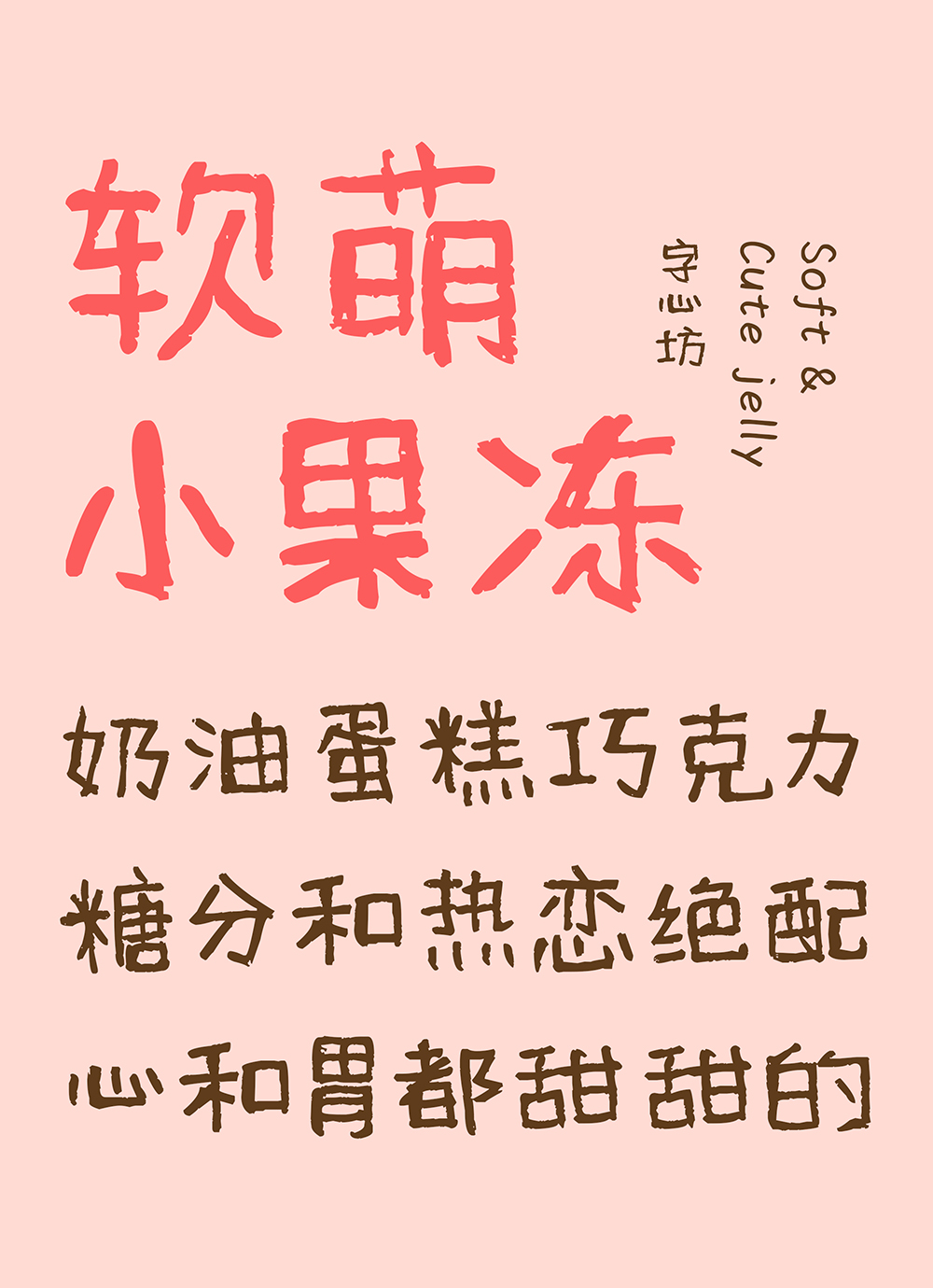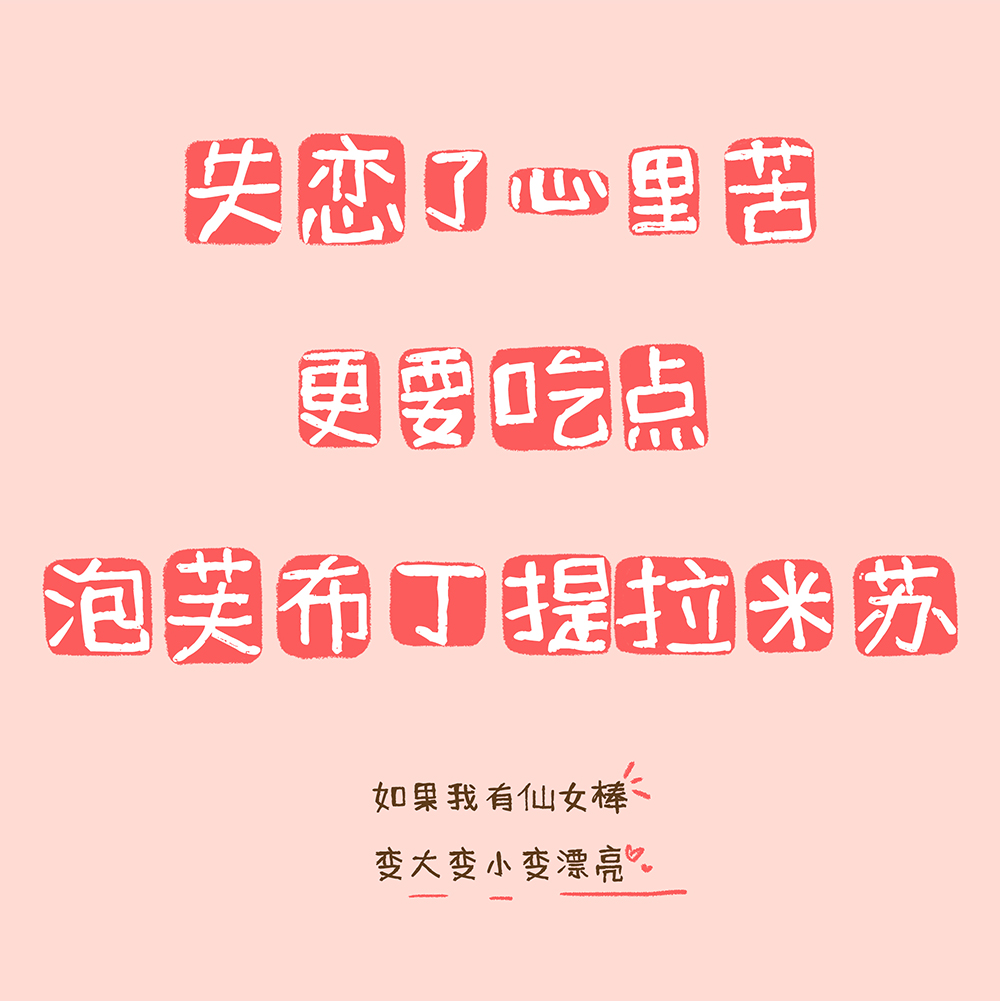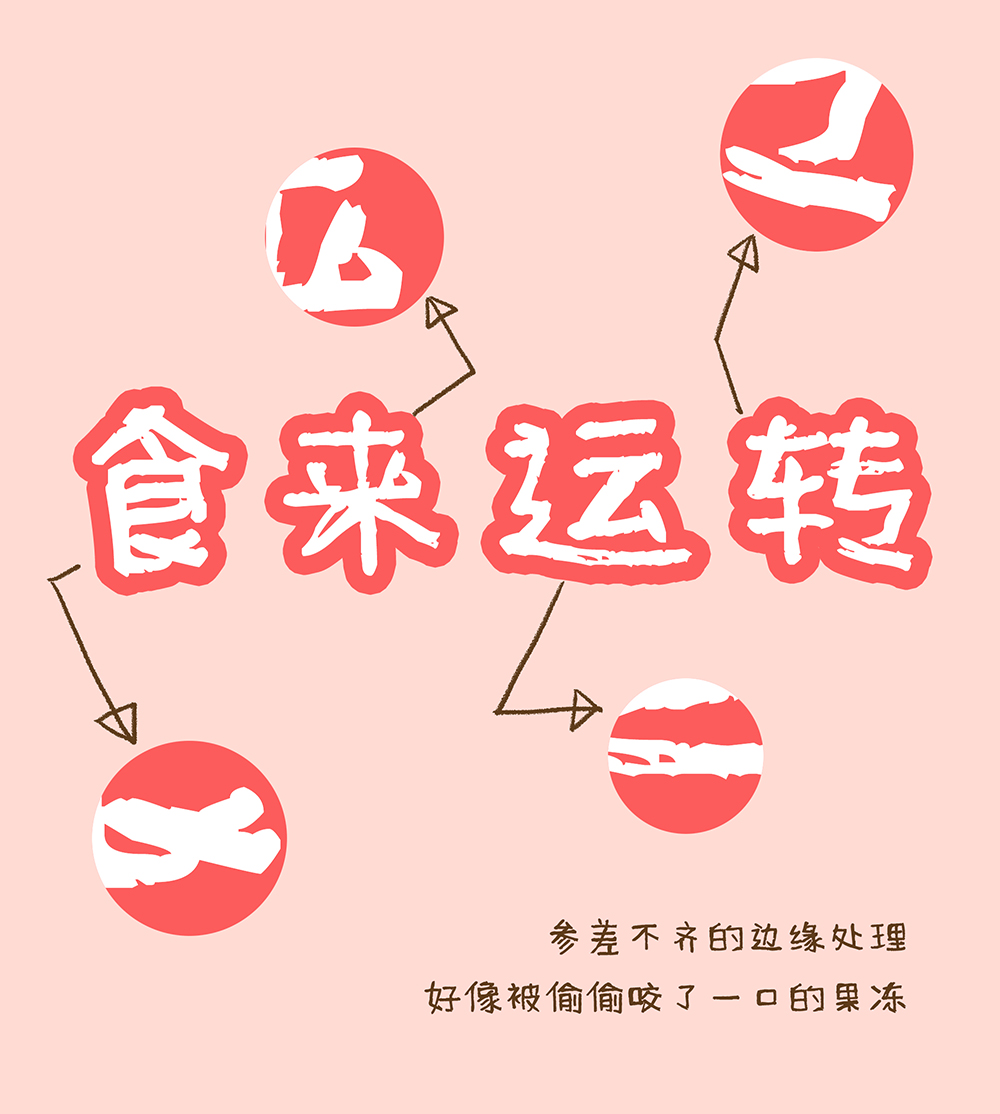
字心坊软萌小果冻
该字体为书法作品,可爱软萌、个性、小清新,造型生动有趣,具有灵活的适用性,天真俏皮又不失时尚感。前期书写过程能充分的反映出创作者心灵对于软萌心境的诠释。后经电脑设计软件进行修正、编辑,最后做成计算机字库。字体风适用于标志、导视、书籍、游戏、动漫、影视、屏显等方面。
字体风格:软萌/ 可爱 / 小清新
推荐场景: 标志 / 导视 / 书籍 / 游戏 / 动漫 / 影视 / 屏显